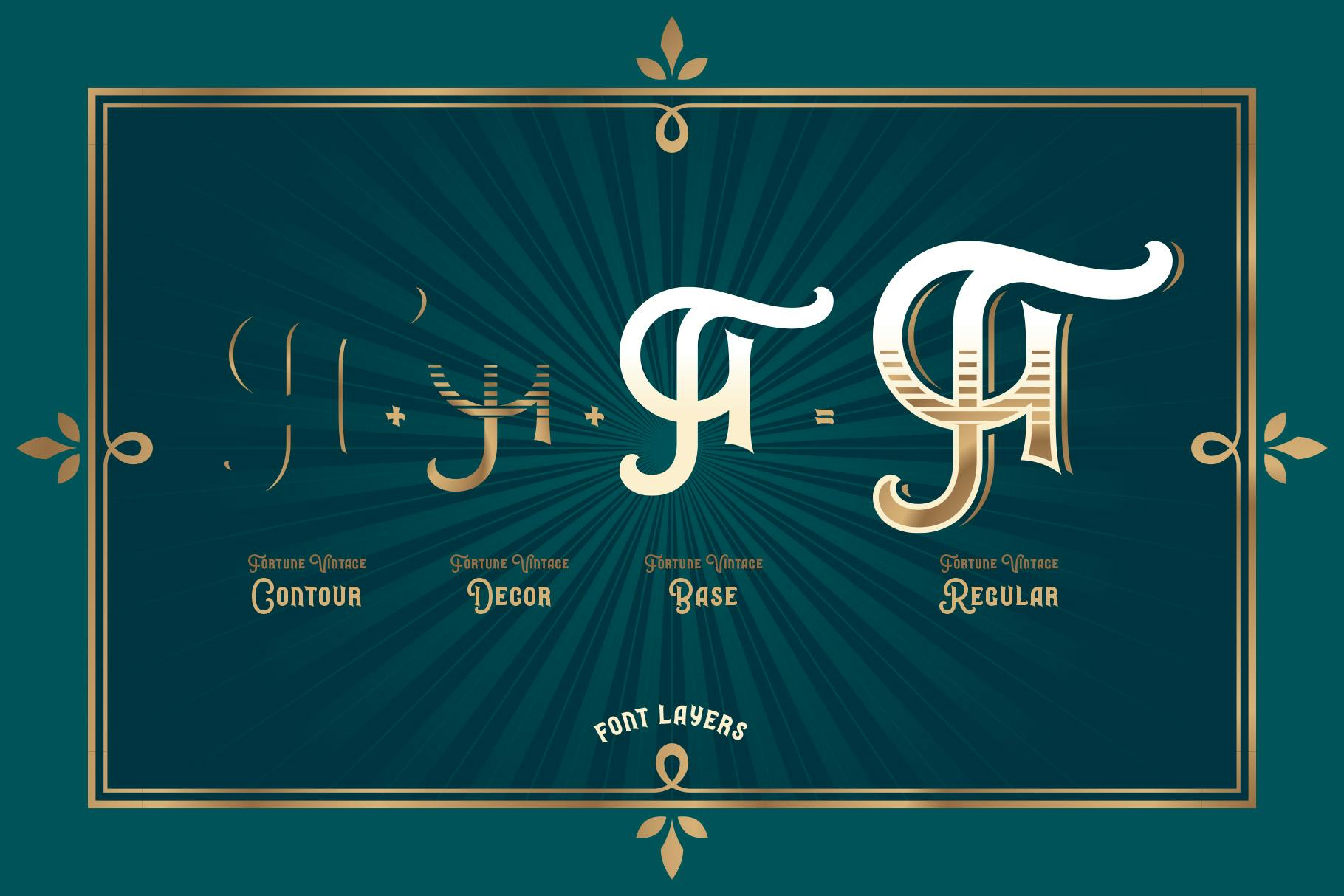
فونت وینتج فورچون یک مجموعه بینظیر از فونتها است که ظاهری قدیمی و کلاسیک با اشکال غربی دارد. این فونت دارای سه لایه برای رنگآمیزی راحتتر است. تمامی حروف کوچک این فونت یک یا دو جایگزین با شکل گسترشیافته در پایین دارند.
فونت وینتج فورچون از اکثر زبانهای اروپایی پشتیبانی میکند و همچنین شامل کاراکترهای سیریلیک اوکراینی است.